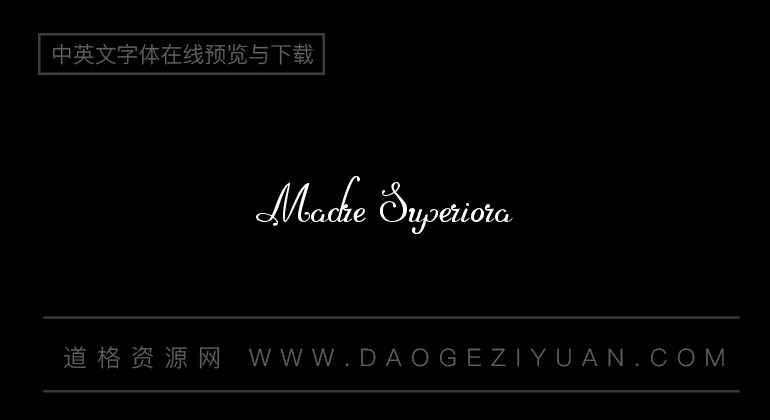
Madre Superiora
Madre Superiora 是一款漂亮的手写风格字体,由TypeTogether设计。它的风格类似于修女日记中的手写字体,因此得名Madre Superiora,意为“修女长老”。 Madre Superiora 字体包含多种字符,包括大写字母、小写字母、数字、标点符号和特殊字符。其手写风格使其在设计中非常实用,可以用于手写风格设计、卡片制作、海报、包装设计和书籍排版等领域。 该字体有多种字重可供选择,从常规到粗体,可以满足不同设计需求。此外,Madre Superiora 还支持多种语言,包括欧洲主要语言和一些非洲语言。 总的来说,Madre Superiora 是一款多功能的手写风格字体,可以为你的设计带来趣味性和独特性。
Madre Superiora是一款非常不错的手写艺术字体,具有很好的视觉感,适合于文化类的宣传设计、商业类品牌的广告和产品包装设计以及个性化文字排版等较多场景。